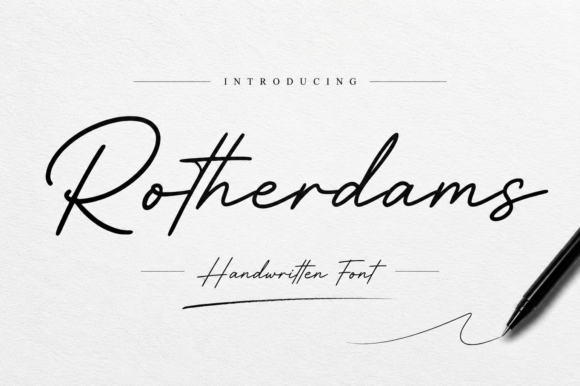
Rotherdams
Rotherdamsのような高品質の素材をお探しの場合、このプレミアムパッケージはクリエイティブなプロジェクトに素晴らしい選択です。
精密に作られたRotherdamsは、クリーンなベクター、滑らかなタイポグラフィ、そして安心のための商用ライセンスを提供します。
POD(オンデマンド印刷)製品、結婚式の招待状、またはソーシャルメディアのグラフィックを作成している場合でも、Rotherdamsは理想的です。